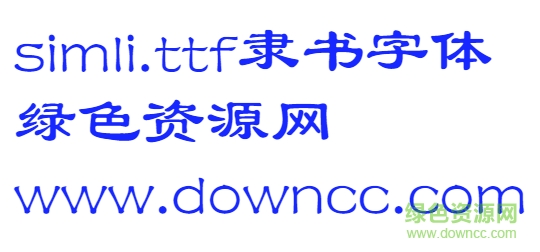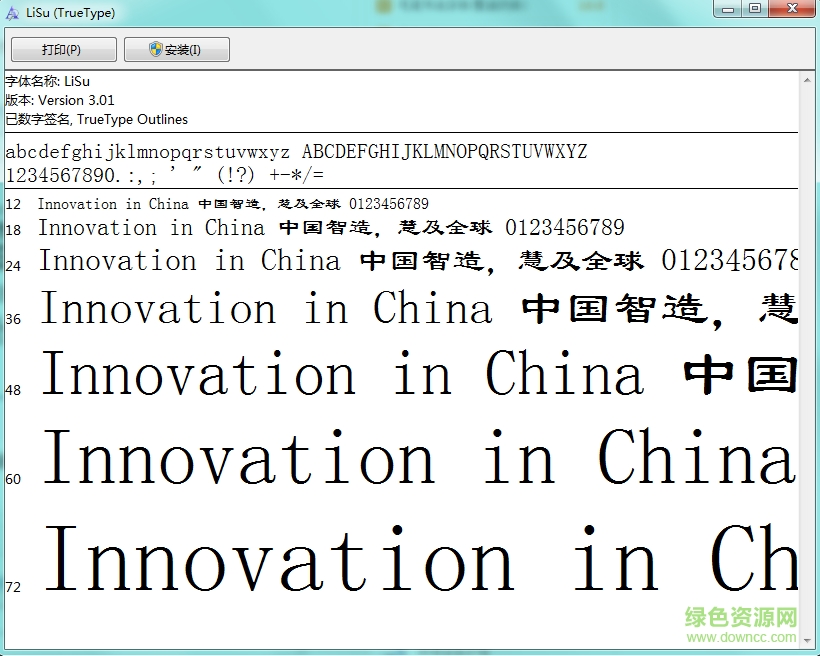
SIMLI是一款隸書字體,在很多游戲中出現(xiàn)比較多,也是Windows系統(tǒng)中的默認(rèn)字體,不小心丟失造成游戲無法正常運(yùn)行也是很麻煩的,在本站重新下載安裝即可解決您的煩惱!
隸書字體是漢字中常見的一種莊重的字體,書寫效果略微寬扁,橫畫長(zhǎng)而直畫短,呈長(zhǎng)方形狀,講究“蠶頭雁尾”一波三折“隸書起源于秦朝,由程邈形理而成,在東漢時(shí)期達(dá)到頂峰,書法界有”漢隸唐楷“之稱。